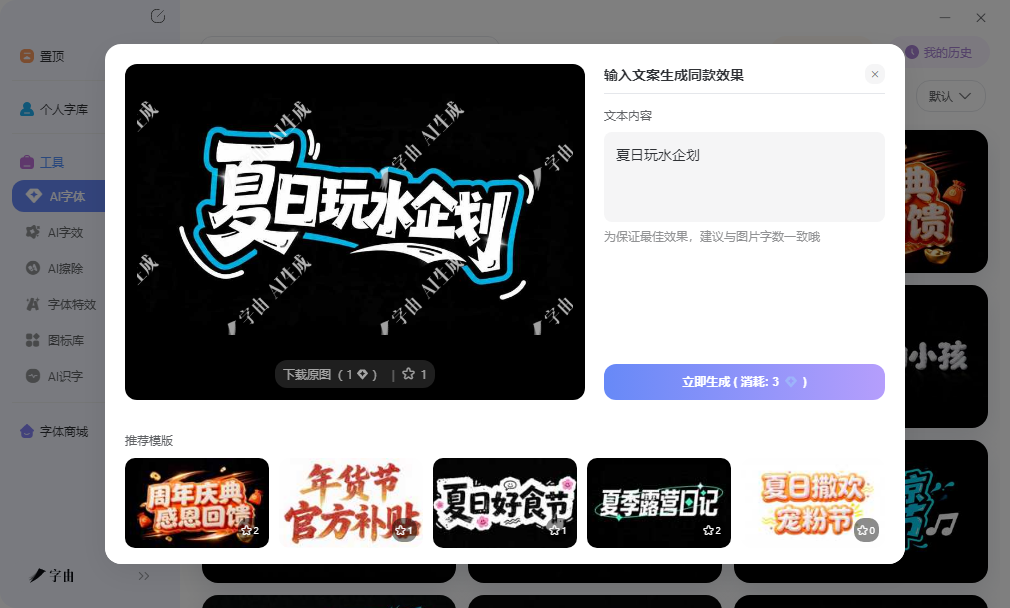
艺术字体设计工具推荐,海报标题瞬间有设计感
海报标题有没有设计感,往往取决于字体选得对不对。常规黑体宋体太平淡,艺术字体又难找,找到了还要会调效果,打开Photoshop调图层样式对很多人来说门槛太高。其实现在有不少工具可以直接出图,输入文案就能拿到带特效的艺术字,保存后拖进海报模板或者PPT里就能用。这篇文章分享的五个渠道,帮你把标题字的设计感往上提一档。
字由的AI字效功能对想做艺术字体但不懂设计软件的人比较友好。打开网页版就能操作,不需要下载安装客户端,临时在别的电脑上也能生成和下载。模板库里有不少视觉冲击力强的风格,立体、霓虹、金属、描边、渐变、投影等十几种大类,每个大类下又有不同细节的变体。想做复古海报就选做旧质感模板,做科技感Banner就选发光效果模板,做电商大促标题就选金色立体模板,风格覆盖比较全。
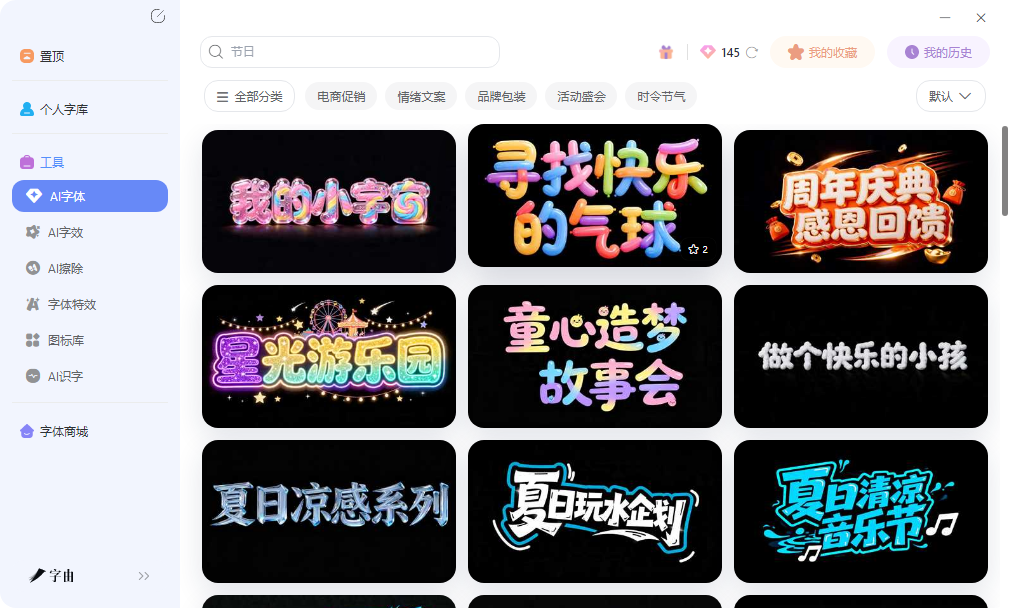
操作上只需要三步:浏览模板、输入文案、点击生成。生成的图片背景透明,直接拖进PS里叠加在背景图层上就能用,不需要抠图。如果已经在PS里铺好了背景图和配图,只差一个标题字,这个字效生成的PNG正好填补缺口。做系列物料时,固定同一款模板分别输入不同文案,风格完全一致,比在传统设计软件里反复复制图层样式要省事得多。
AI字效支持在网页版里直接使用。基础面板调节字号和粗细,进阶面板调整配色和效果强度,个性化空间比较足。免费用户每日有算力额度,登录赠送的点数足够应付日常轻量使用。预览区支持先输入文案查看效果,满意了再正式生成,预览环节不消耗额度,这个设计对轻度用户比较友好,可以反复试到合适为止。
字由的艺术字体分类也比较实用。创意分类下有不少风格强烈的展示字体,笔画带有装饰性细节;文艺分类偏向优雅精致,适合做展览标题或者高端包装。预览框支持输入自己的文案,调整到实际使用字号后查看效果,确认清晰度再激活,避免了装完发现不合适再卸载的反复操作。激活后字体直接出现在设计软件里,不需要重启程序。
TextFancy是一个文字生成器,专注装饰性字体效果。输入文字后,系统会转换为多种美化样式,包括泡泡字、涂鸦体、立体字等。这些效果可以直接复制为Unicode字符,在社交媒体和聊天软件里使用,也可以生成图片格式下载。
作为艺术字体设计的渠道,它的优势在于风格活泼、操作简单,适合快速出一张带装饰效果的文字图。网站上还提供了多种参数调节选项,可以微调效果的强度和细节。对于做轻松活泼的内容,比如儿童品牌、亲子活动或者文创设计,这里的风格比较贴切。生成速度较快,不需要注册就能使用,流程顺畅。
FontsGeek是一个精选字体下载平台,收录了不少艺术风格的字体文件。分类体系比较细致,可以按风格标签逐步筛选,从基础无衬线体到装饰性强的展示字体都有覆盖。每款字体都有预览图和下载按钮,部分还展示了完整的字符集。
作为艺术字体设计的资源库,它的优势在于字体质量经过一定筛选,下载后安装到系统就能在设计软件里调用。和在线生成图片的工具不同,FontsGeek提供的是可安装的字体文件,后期可以在Photoshop、Illustrator等软件里进行完整的排版编辑,调整字距、行距、颜色等参数,灵活性更高。对于需要深度排版、而不是直接套用图片的设计师来说,这里的资源比较实用。下载的字体文件为标准TTF或OTF格式,兼容性没有问题。
ActionFonts专注特效字体生成,风格偏向视觉冲击力强。网站上的模板包括火焰、金属、冰晶、雷电等方向,适合做游戏海报、活动宣传图或者电商大促标题。输入文案后选择模板,系统生成带特效的图片,效果比较夸张,辨识度很高。
作为艺术字体设计的工具,它的优势在于效果层次丰富,常规字体文件本身不具备这些视觉特征。生成的图片可以直接下载使用,部分高级效果需要付费,但免费版本的基础特效对一般海报场景已经够用。对于需要强烈视觉吸引力的项目,比如游戏宣传、音乐节海报或者促销活动,这里的特效风格比较匹配。操作流程简洁,不需要任何设计基础,几分钟内就能拿到成品图。
StylishFont.io 目前收录了超过200种装饰字体样式。输入普通文本后,系统会实时转换为多种Unicode装饰字符,包括草书、粗体、双线体、小型大写字母、泡泡字、Zalgo故障风、中世纪哥特体等。
操作上比较直接,在输入框里打字,下方会列出所有可用的样式变体。网站支持自定义收藏夹功能,可以把常用的字体样式固定在页面顶部,方便下次快速访问。还提供了文本装饰器,可以对生成的文字进一步添加下划线、删除线、波浪线等效果。
作为艺术字体设计的渠道,它的优势在于样式数量多、支持200多种风格,且提供了字号滑块预览功能,可以调整大小后观察效果。生成的Unicode字符可以直接复制粘贴到社交媒体、聊天软件或者文档中使用,不需要生成图片文件。免费使用,不需要注册,打开网页就能操作。
如果说你想要出一张带设计感的海报标题,字由的AI字效配合字体库,从选字形到加特效几分钟就能拿到成品图,作为艺术字体设计的主力渠道效率不错。FontGenerator.co的装饰性文字适合社交媒体直接使用,ActionFonts的火焰金属特效适合游戏和活动海报,FontsGeek的精选字体文件适合在设计软件里深度排版,TextFancy的泡泡涂鸦风格适合轻松活泼的场景。工具选对了,海报标题的设计感自然就上来了。